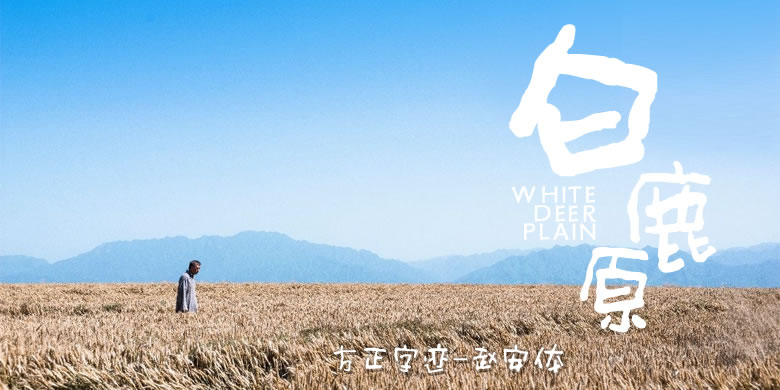
方正字迹-赵安体
方正字迹-赵安体,是一款以传统篆隶笔画书写当代个性的字体。其笔画角度多变,结构上松下紧,特点鲜明识别性强。有种朴拙透巧稚气顽皮的特点,有沉静纸面上浮躁骚动的韵味,可谓是时下社会的生态使然。赵安在书法实践中,因身陷名利圈中,提笔面对宣纸,心态浮躁与沉静相互交错,信手涂鸦和潜心笔墨轮番更替,对前人书写性情,书为心声的体味尤为深刻。以力求与人不同开始,到逐渐形成了自己的风格,实属无心插柳之举。